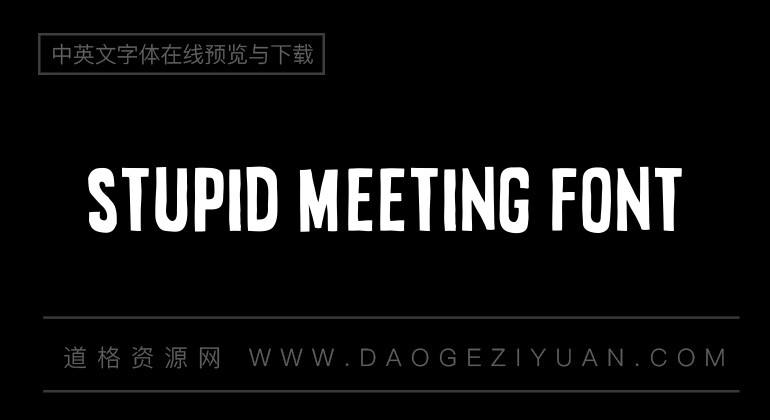
Stupid Meeting Font
Stupid Meeting Font 是一种由设计师 Chris Simpkins 创造的字体,旨在用于打印与会议相关的材料,例如议程、会议记录和幻灯片等。 该字体的设计理念是在确保清晰易读的同时,打破传统字体的枯燥和枯燥。因此,Stupid Meeting Font 采用了一种带有斜杆的不对称字体,使其看起来更加有趣和富有活力。 此外,该字体有着宽大的字母间距和较小的字形大小,这使得它在打印材料时非常适合,而且非常易于阅读。 总的来说,Stupid Meeting Font 是一种令人印象深刻的字体,它可以使您的会议材料更加引人注目,同时确保其易于阅读和理解。
Stupid Meeting Font是一款非常不错的手写艺术字体,具有很好的视觉感,适合于文化类的宣传设计、商业类品牌的广告和产品包装设计以及个性化文字排版等较多场景。